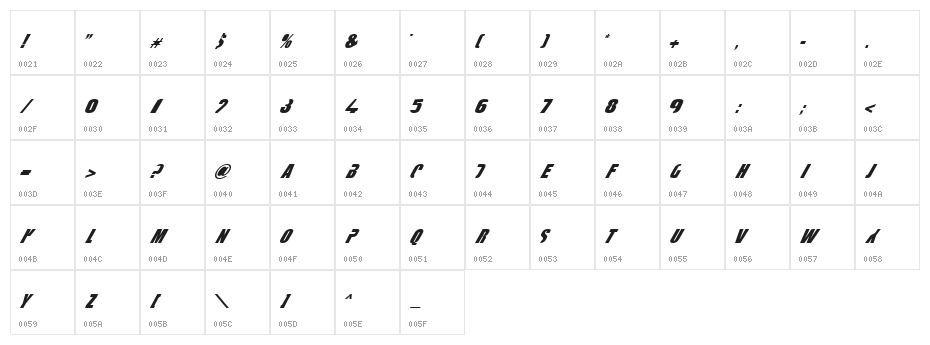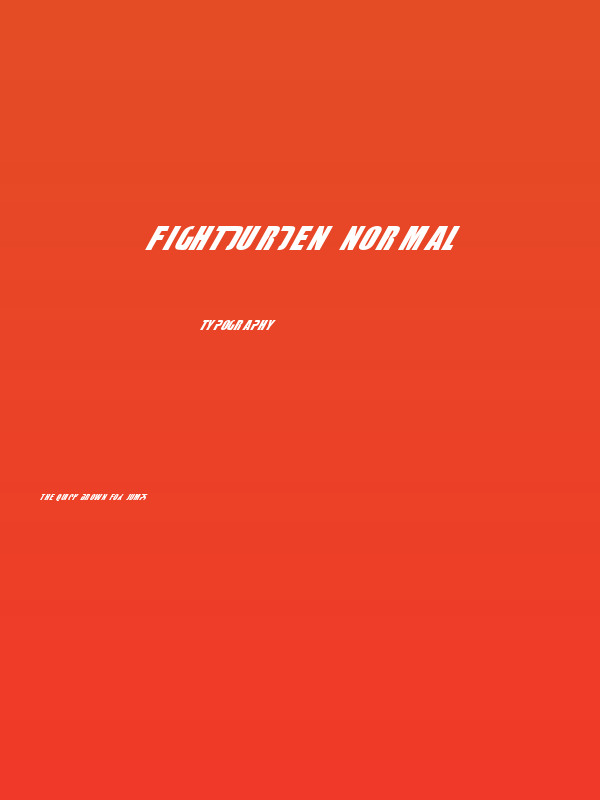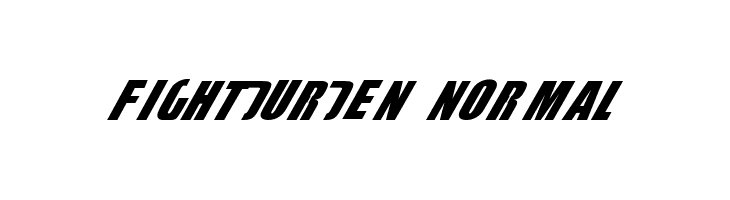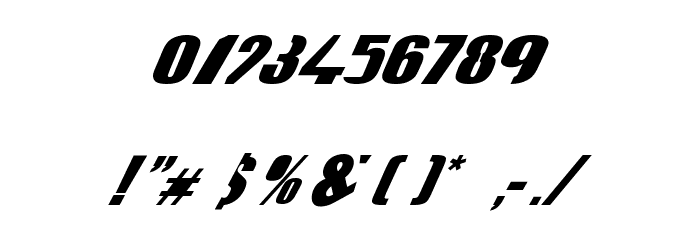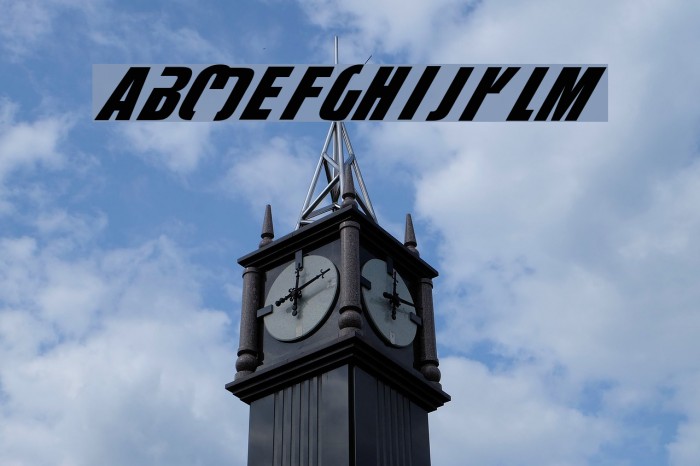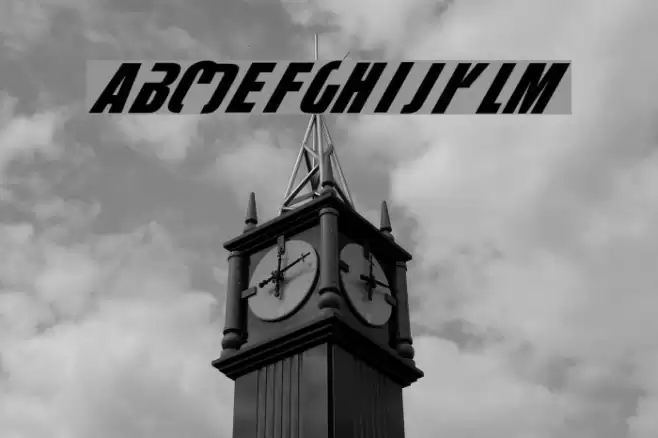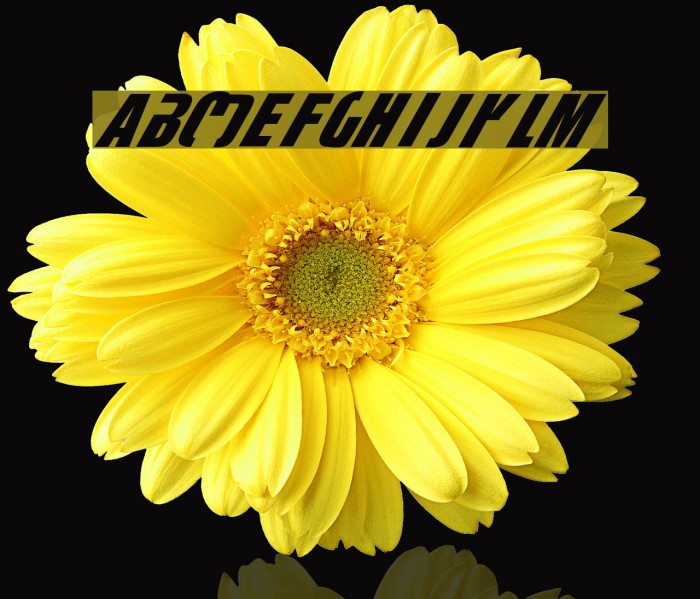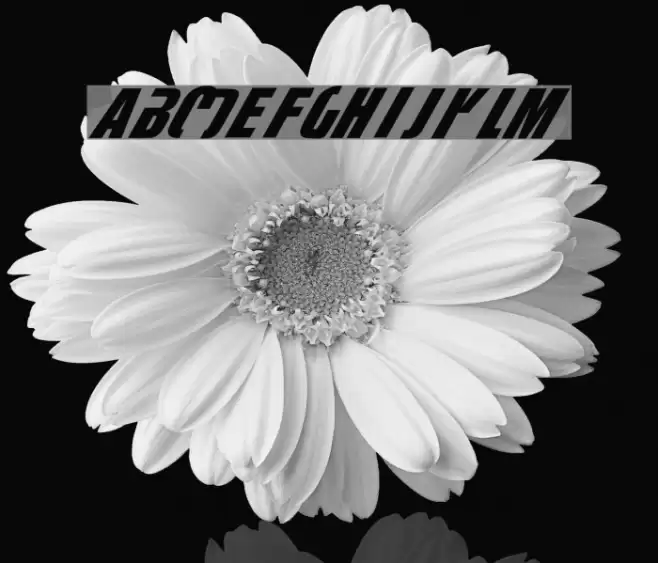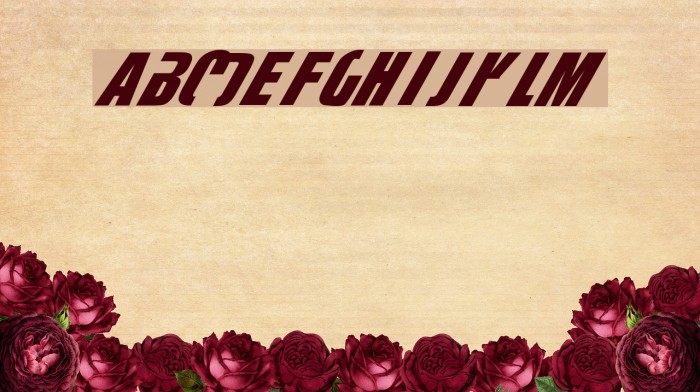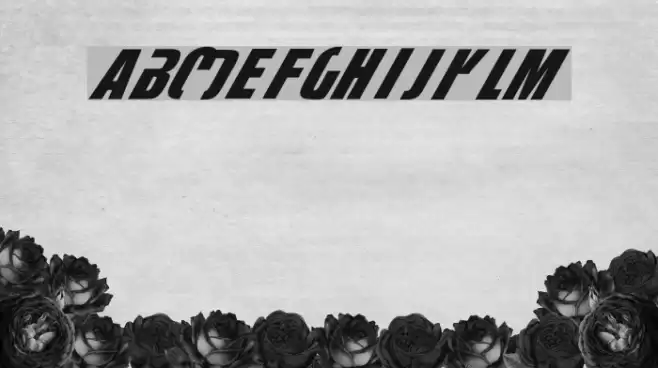
fightDurden Normal Font
| الاسم | fightDurden Normal |
| الوزن | Normal |
| الفئات | Capitals |
| العرض | Condensed |
| مشاريع مقترحة | Ideal for sports branding, action movie posters, dynamic logos, and edgy apparel designs. |